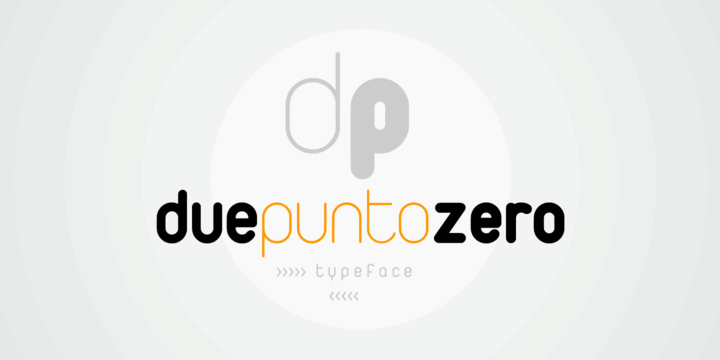
Duepuntozero Font
A Duepuntozero é uma fonte sans-serif arredondada criada para adicionar um toque contemporâneo aos logos e cabeçalhos de marcas que se iniciam com números 2.0, bem como ao design do layout do seu site ou aplicativo, especialmente em cenários onde há destaque. Inspirada nas últimas redes sociais e aplicações de mensagens instantâneas, a Duepuntozero oferece um ar sofisticado que combina perfeitamente com os ambientes digitais modernos. Para uso comercial, é recomendável obter uma licença gratuita através do site da ZetaFonts em: http://www.zetafonts.com/duepuntozero. Esta fonte Display é ideal para criar um visual atraente e atualizado que se alinha perfeitamente com o design de marcas atuais e futuristas.